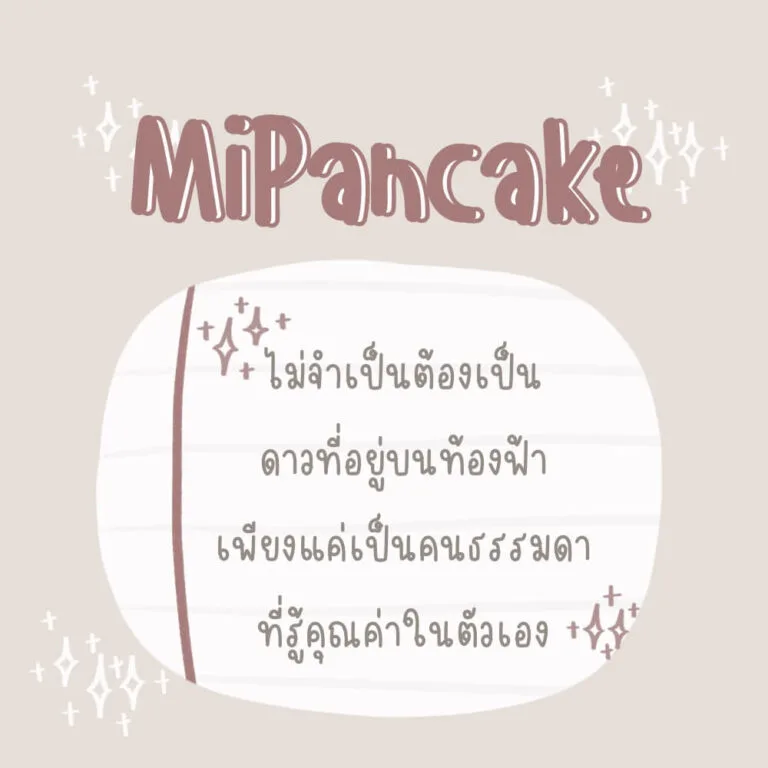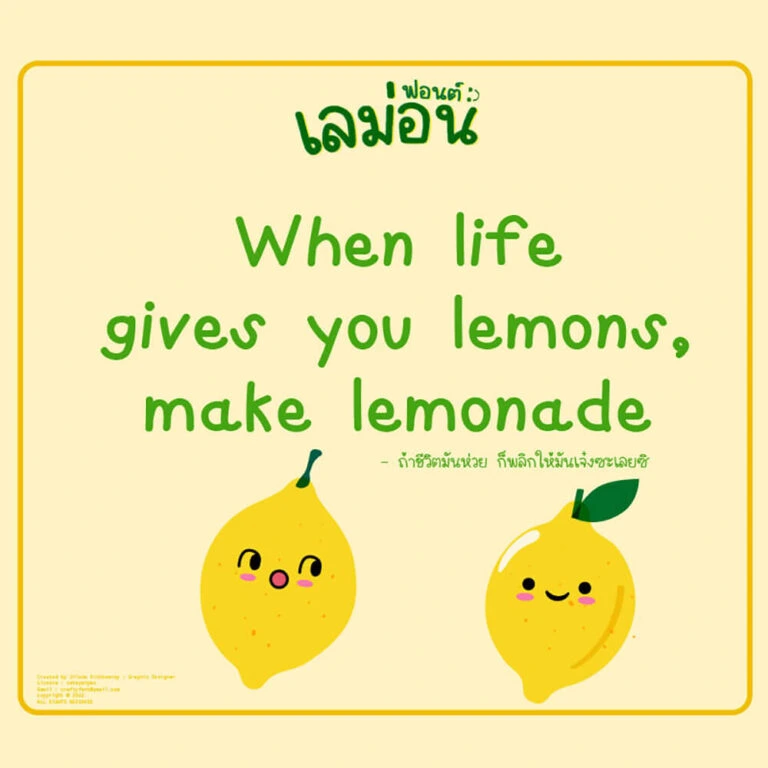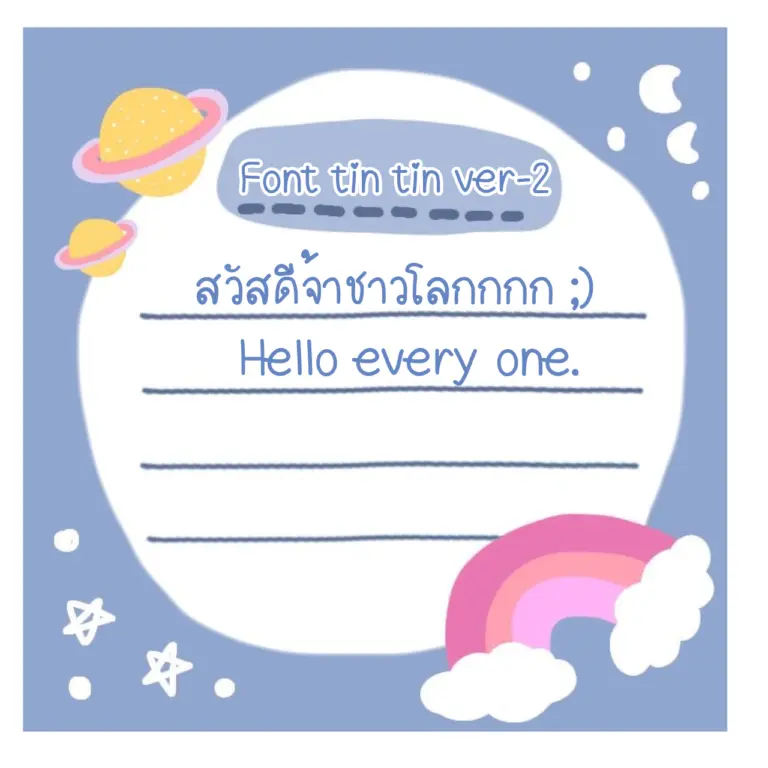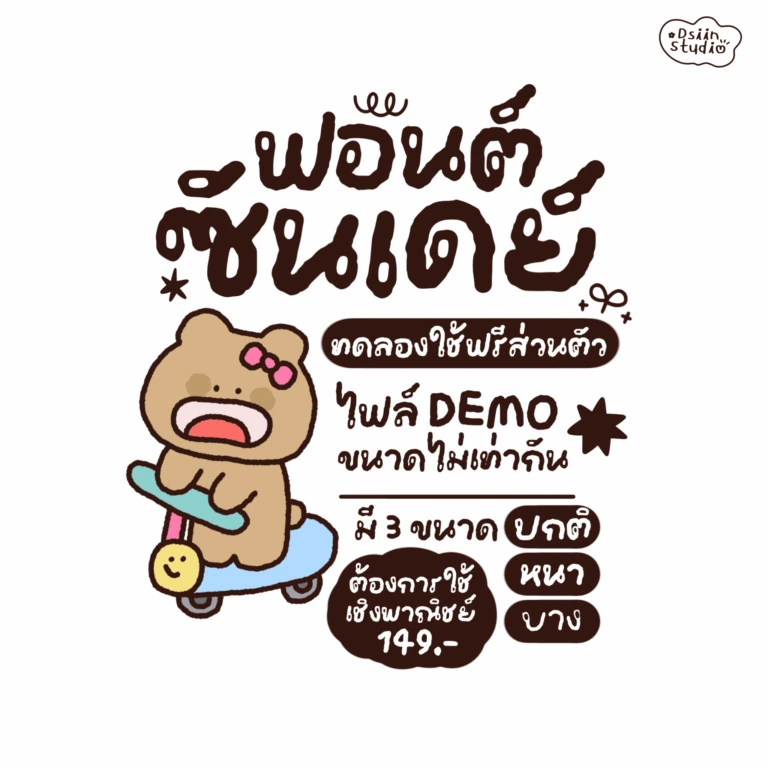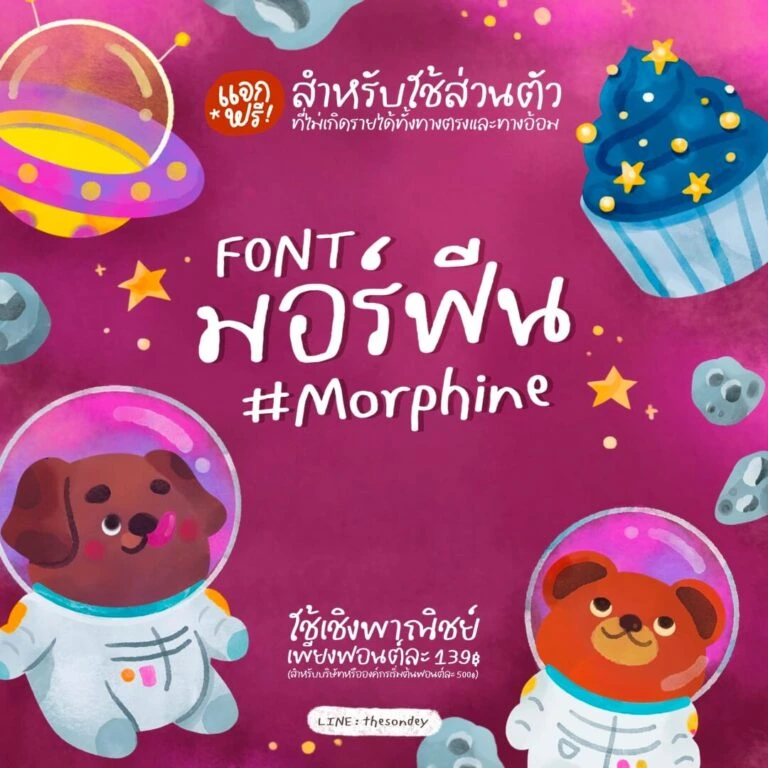
ฟอนต์ไทยที่สวยงามและมีเอกลักษณ์เป็นองค์ประกอบสำคัญในการสร้างคอนเทนต์ให้โดดเด่น ไม่ว่าจะเป็นงานกราฟิก งานนำเสนอ หรือโปรเจกต์ดิจิทัลต่าง ๆ การเลือกฟอนต์ที่เหมาะสมจะช่วยสื่อสารบุคลิกของแบรนด์และดึงดูดความสนใจของผู้ชม บทความนี้รวบรวมฟอนต์ไทยฟรี 70 แบบ ที่นักสร้างคอนเทนต์สามารถนำไปใช้ได้ทันที พร้อมวิธีดาวน์โหลดและติดตั้งอย่างละเอียด
แจก 70 ฟอนต์ไทยสวย ๆ ฟรี อัปเดตล่าสุด 2026
ฟอนต์ลายมือและฟอนต์แนวสร้างสรรค์
กลุ่มฟอนต์ที่ผสมผสานเสน่ห์ของลายมือมนุษย์เข้ากับจินตนาการในการออกแบบ สื่อถึงอารมณ์ ความเป็นกันเอง หรือเอกลักษณ์เฉพาะตัว เหมาะสำหรับงานศิลปะ โปสเตอร์ แบรนด์ที่ต้องการสร้างความแตกต่างอย่างมีสไตล์
Maaja (หมาจ๋า)
ฟอนต์ลายมือที่ให้ความรู้สึกเป็นกันเองและสนุกสนาน เหมาะสำหรับงานออกแบบที่ต้องการความเป็นมิตร
SanamDeklen_chaya (สนามเด็กเล่น)
ฟอนต์ที่มีลักษณะคล้ายลายมือเด็ก ให้ความรู้สึกสนุกสนานและไร้เดียงสา เหมาะสำหรับงานที่เกี่ยวข้องกับเด็กหรือการศึกษา
iannnnn-DOG (หมา)
ฟอนต์ลายมือที่มีความเป็นธรรมชาติและเป็นกันเอง เหมาะสำหรับงานที่ต้องการความรู้สึกอบอุ่น
Itim
ฟอนต์ลายมือแบบสบาย ๆ ให้ความรู้สึกเป็นกันเอง เหมาะสำหรับงานที่ไม่เป็นทางการ
Mali
ฟอนต์ลายมือที่อ่านง่าย เหมาะกับงานเล่าเรื่องและบทความที่มีความยาว
Passadoo (พัสดุ)
ฟอนต์ที่มีลักษณะเป็นลายมือ สื่อถึงความเป็นกันเองและเรียบง่าย ใช้ได้ดีกับงานบล็อกและโซเชียลมีเดีย
Layiji RuDuuRon (ฤดูร้อน)
ฟอนต์ที่มีลักษณะเป็นลายมือ สื่อถึงความอบอุ่นและเป็นธรรมชาติ เหมาะกับงานที่ต้องการบรรยากาศสบาย ๆ
was@bubphasawan (วัสบุปผาสวรรค์)
ฟอนต์ลายมือที่มีความเป็นธรรมชาติ เหมาะสำหรับงานที่ต้องการความรู้สึกอ่อนโยน
Layiji Sarangheyo (เลย์อิจิ ซารังเฮโย)
ฟอนต์ที่มีลักษณะน่ารักและเป็นกันเอง เหมาะสำหรับงานที่ต้องการสื่อถึงความรักและความอบอุ่น
Kart-CHAWANSILP (เคอาร์ต ชวาลศิลป์)
ฟอนต์ที่มีลักษณะเป็นลายมือ สื่อถึงความคิดสร้างสรรค์และความเป็นศิลปะ เหมาะกับงานดีไซน์
FkApril
ฟอนต์ลายมือที่มีเส้นสายพลิ้วไหว ให้ความรู้สึกอบอุ่นและเป็นกันเอง เหมาะกับงานเชิงสร้างสรรค์
MiPancake
ฟอนต์ลายมือกลมมนคล้ายขนมแพนเค้ก เหมาะกับงานที่ต้องการความน่ารักและความหวาน
เลม่อน (Lemon)
ฟอนต์ลายมือโทนสดใส ให้ความรู้สึกเปรี้ยวซ่าและสนุกสนาน เหมาะกับงานออกแบบวัยรุ่น
tintin ver-2
ฟอนต์ลายมือที่ให้ความรู้สึกขี้เล่นและทันสมัย เหมาะกับงานการ์ตูนและงานเด็ก
อั่งเปา (TCS4HongBao)
ฟอนต์ลายมือที่ผสมความเป็นเอเชียตะวันออก ให้ความรู้สึกอบอุ่น เหมาะกับงานเทศกาลและการ์ดอวยพร
ซันเดย์ (DS Sunday)
ฟอนต์ลายมือสบาย ๆ ให้ความรู้สึกผ่อนคลาย เหมาะสำหรับงานออกแบบที่ไม่เป็นทางการ
มอร์ฟีน (PG Morphine)
ฟอนต์ลายมือเส้นคมที่ให้ความรู้สึกทันสมัย เหมาะกับงานที่ต้องการความโดดเด่นและดึงดูดสายตา
ฟอนต์ไทย มาตรฐานและฟอนต์ทั่วไป
ฟอนต์ในกลุ่มนี้ออกแบบตามเกณฑ์มาตรฐานการใช้งาน เหมาะกับเอกสารราชการ งานวิชาการ หรือสื่อที่เน้นความอ่านง่ายและความเป็นกลาง สามารถประยุกต์ใช้ได้หลากหลายประเภทงาน
นูร่าทับทิม
ฟอนต์ที่มีความเรียบง่ายแต่โดดเด่น เหมาะสำหรับใช้ในงานทั่วไปทั้งงานพิมพ์และดิจิทัล ช่วยให้ข้อความอ่านง่ายและชัดเจน
FC Fast (เอฟซี ฟาสต์)
ฟอนต์ที่มีลักษณะเรียบง่ายและทันสมัย เหมาะสำหรับงานที่ต้องการความรวดเร็ว
เอฟซี เมอเตอร์เวย์
ฟอนต์ที่มีดีไซน์สมัยใหม่และเรียบหรู เหมาะสำหรับงานที่ต้องการความทันสมัยและโดดเด่น เช่น โลโก้หรือการออกแบบกราฟิก